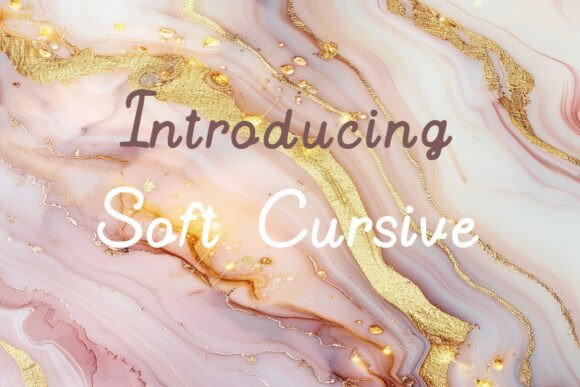
Soft Cursive
Soft Cursive – La police cursive qui allie flexibilité et grâce
Découvrez Soft Cursive, la typographie manuscrite idéale pour sublimer vos projets créatifs. Grâce à son équilibre parfait entre souplesse et élégance, elle s’adapte à une multitude d’applications, du textile aux supports numériques.
- Design de t‑shirts : apporte une touche raffinée et tendance à chaque vêtement.
- Magazines et publications : confère un style classique et intemporel aux titres et accroches.
- Identité de marque : renforce la personnalité de votre logo avec un charme inimitable.
- Stickers personnalisés : donne vie à vos autocollants avec une écriture fluide et chaleureuse.
- Cartes de vœux : ajoute une note sincère et émotive à chaque message.
- Projets Cricut : sublime vos découpes et gravures grâce à sa lisibilité impeccable.
- Contenu digital : idéal pour les publications sociales, les affiches percutantes et les fichiers SVG qui captivent l’audience.
En choisissant Soft Cursive, vous optez pour une police qui crée immédiatement un lien émotionnel avec votre public. Son allure sophistiquée et son pouvoir d’attraction transforment chaque création en une œuvre mémorable, difficile à ignorer. Adoptez-la dès maintenant et laissez vos designs respirer l’élégance et le charme intemporel.